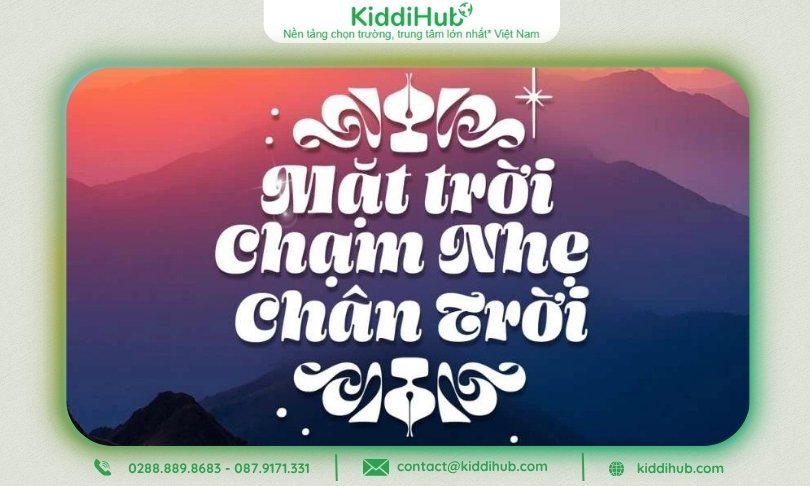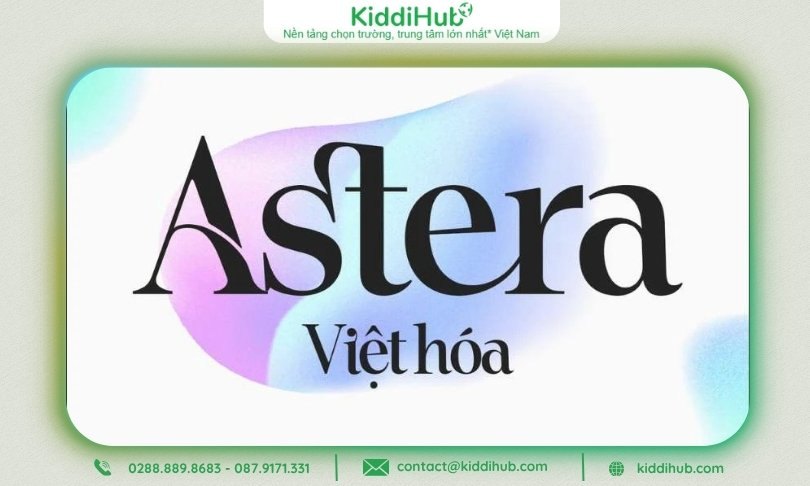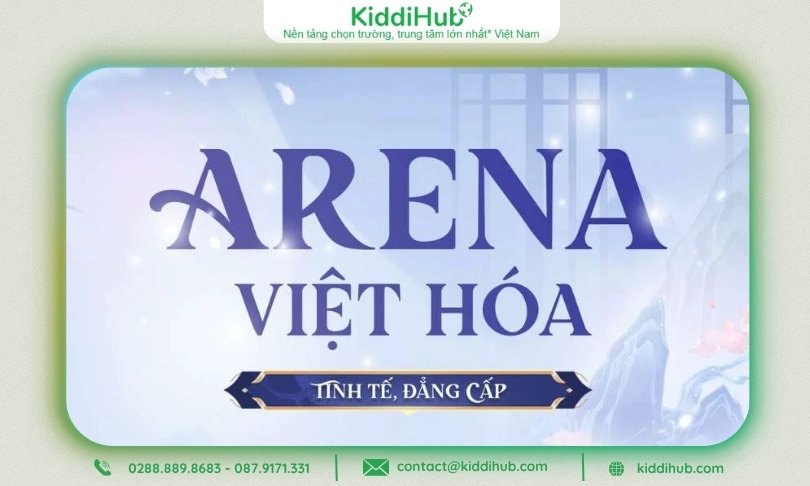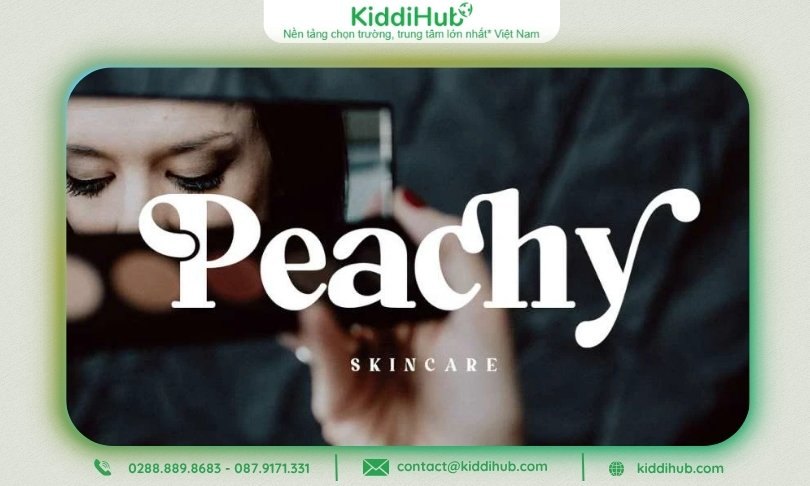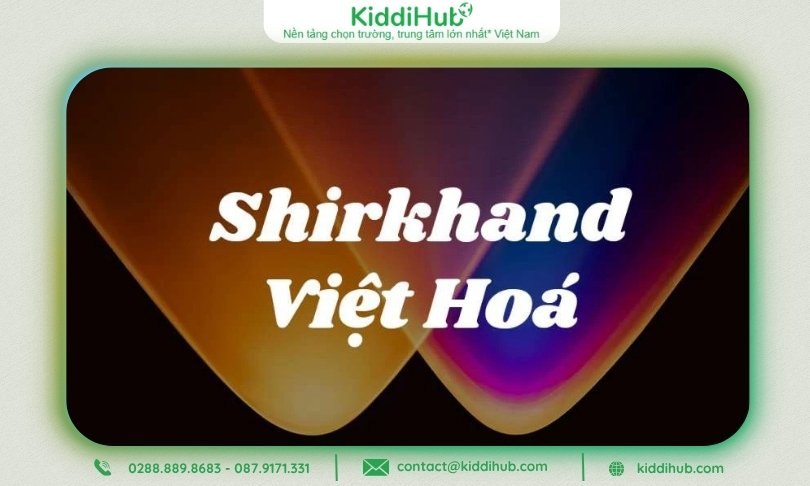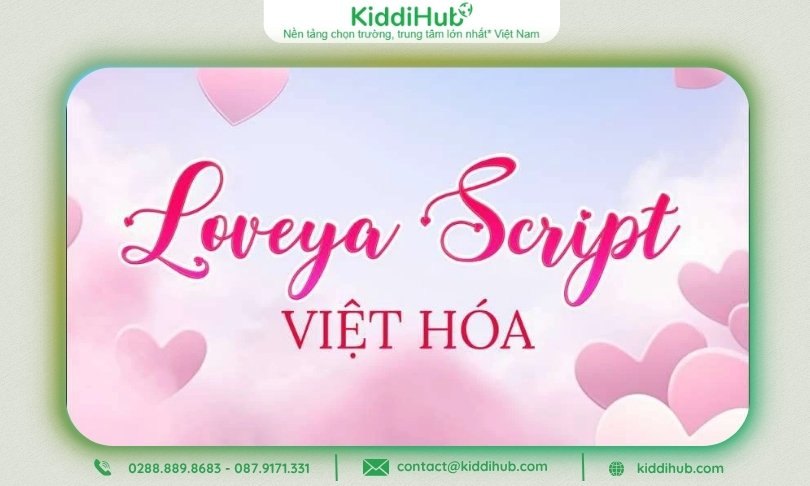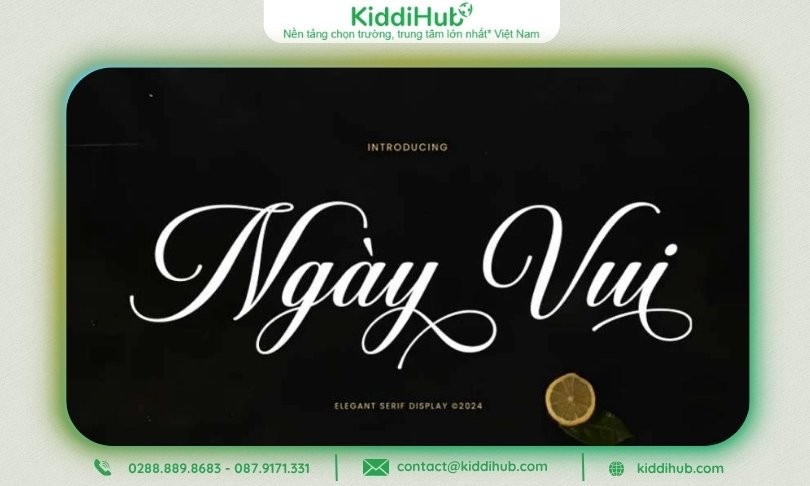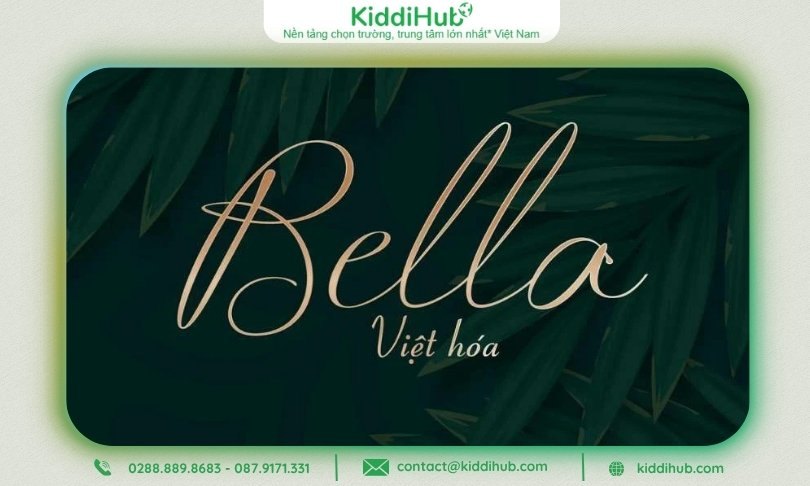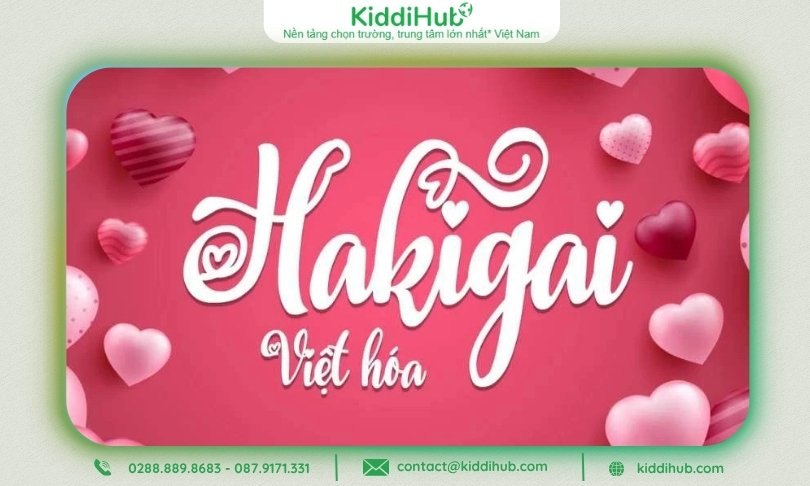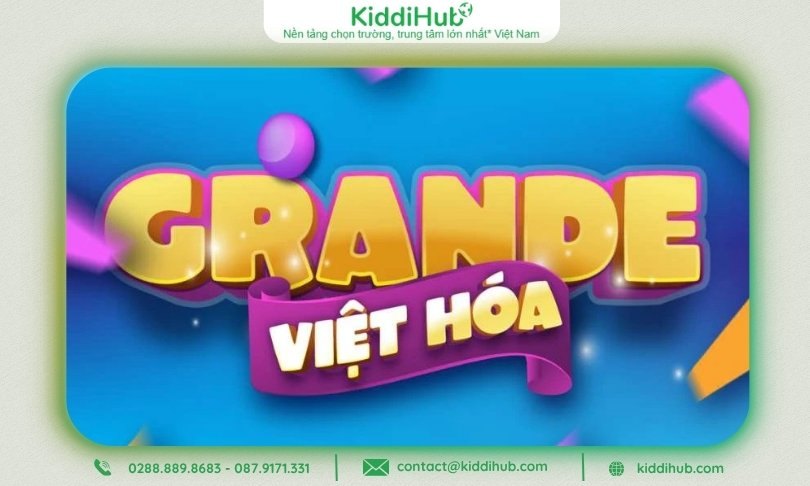
Font chữ 20/10 là chi tiết nhỏ nhưng lại mang sức mạnh lớn trong việc truyền tải cảm xúc. Dù là thiệp chúc, slide, poster hay video tri ân, lựa chọn đúng phông chữ sẽ giúp thiết kế thêm tinh tế & ấn tượng. Mỗi kiểu chữ đều có “tính cách” riêng – trang trọng, ấm áp hay trẻ trung – góp phần làm nổi bật thông điệp cùng với tinh thần tôn vinh phái đẹp ngày 20/10.
Tuyển tập phông chữ 20/10 Việt hóa dưới đây là “kho báu” cho những ai muốn tạo ra thiết kế chúc mừng đẹp, chuyên nghiệp trong năm 2025. Việc dùng font Việt hóa không chỉ giúp bạn gõ tiếng Việt có dấu mượt mà, tránh lỗi hiển thị mà còn giữ cảm xúc, tinh thần bản gốc của kiểu chữ.
Dù đang chuẩn bị thiệp mời, poster, slide công ty hay làm video tri ân phụ nữ, các font dưới đây đều mang nét riêng giúp tôn thông điệp của bạn.
DVN Lively là font script mềm mại, mang hơi thở nhẹ nhàng & thân thiện. Đường nét uốn lượn vừa phải, các chữ cái bo tròn tạo nên cảm giác gần gũi, tươi tắn.
Font chữ 20/10 này rất hợp với thiệp chúc, ảnh cover Facebook hoặc slide cảm ơn trong Ngày Phụ nữ Việt Nam. Khi phối, bạn có thể kết hợp DVN Lively với font sans-serif đơn giản như Montserrat hay Nunito cho phần nội dung để giữ bố cục hài hòa, hiện đại.
DVN Astera thuộc nhóm serif thanh lịch, có chân chữ nhẹ & tỷ lệ cân đối. Các chi tiết nhỏ trong chữ đem tới cảm giác tinh tế, rất phù hợp phong cách sang trọng, chuyên nghiệp.
Bạn hãy sử dụng Astera cho bìa thiệp mời, poster sự kiện công ty hay slide kỷ niệm. Khi đặt trên nền kem, vàng nhạt, hồng phấn, font chữ 20/10 này càng tôn lên vẻ trang nhã, thể hiện sự trân trọng dành cho phái đẹp.
Nếu bạn muốn gây ấn tượng mạnh ngay từ tiêu đề, DVN ARENA là chọn lựa lý tưởng. Font sở hữu độ dày vừa phải, đường nét mạnh mẽ nhưng vẫn có góc bo mềm để tránh cảm giác cứng nhắc.
ARENA rất hợp cho banner chúc mừng 20/10, poster sân khấu hoặc slide mở đầu. Đây là font chữ 20/10 giúp cân bằng giữa sức mạnh & sự tinh tế – tôn vinh hình ảnh người phụ nữ hiện đại vừa mạnh mẽ, vừa duyên dáng.
Sophia Beauty được thiết kế với cảm hứng từ sự dịu dàng & sang trọng. Kiểu chữ có độ cong mềm, giãn cách ký tự tinh tế, giúp cho thiết kế trông nhẹ nhàng mà vẫn cuốn hút.
Font chữ 20/10 này cực kỳ phù hợp cho logo thương hiệu mỹ phẩm, bìa thiệp hay ảnh tri ân. Khi kết hợp với hoa văn nhẹ cùng màu pastel(hồng phấn, be, hoặc lavender), Sophia Beauty tạo tổng thể tinh tế, đậm chất “feminine luxury”.
Shrikhand là font script đậm, nét dày & cực kỳ ấn tượng. Mỗi ký tự như có “trọng lượng”, tạo điểm nhấn mạnh mẽ, cuốn hút. Hãy dùng Shrikhand cho tiêu đề khẩu hiệu, slide mở màn video hay chữ trang trí trong poster.
Lưu ý, bạn không nên dùng font chữ 20/10 này cho nội dung dài. Hãy để nó làm “ngôi sao chính” trong bố cục để tôn trọng phong thái cá tính cùng sự tự tin của người phụ nữ Việt.
Font chữ 20/10 viết tay mang hơi thở truyền thống là chọn lựa hoàn hảo cho những ai muốn tạo thiết kế gần gũi, giàu cảm xúc & mang đậm dấu ấn cá nhân. Phông chữ viết tay không chỉ gợi lại hình ảnh của nét bút xưa – mộc mạc, chân thành – mà còn giúp lời chúc 20/10 thêm ấm áp, tinh tế.
Dưới đây là 3 kiểu chữ viết tay Việt hóa nổi bật, phù hợp cho thiệp, khung ảnh, slide video hay ấn phẩm tri ân trong dịp đặc biệt này.
Loveya Script mang phong cách viết tay nhẹ nhàng, các nét chữ nối liền mượt mà như dòng mực chảy. Font chữ 20/10 này có chi tiết nhỏ xinh như trái tim hay dấu chấm mềm mại, giúp thiết kế trở nên sinh động & giàu cảm xúc.
Phông chữ này rất thích hợp cho thiệp cá nhân, lời chúc dành cho mẹ, vợ hoặc người yêu. Khi dùng, bạn nên chọn kích thước chữ lớn cho tiêu đề, kết hợp với font sans-serif gọn gàng cho phần nội dung để tổng thể dễ đọc và hài hòa.
Peristiwa gợi nhớ nét bút thư pháp cổ điển, với độ dốc nhẹ cùng cấu trúc chữ chắc chắn. Cảm giác khi nhìn là sự trang trọng, mộc mạc – rất phù hợp cho lời chúc tặng mẹ, thiệp tri ân cô giáo hay sự kiện truyền thống trong trường học, công ty.
Khi in, bạn hãy chọn chất liệu giấy matt hoặc giấy có vân để tăng hiệu ứng “chữ in tay”, đem tới cảm giác sang trọng và chân thật.
DVN Bella là kiểu chữ thanh thoát, mảnh mai, mỗi nét như được viết bằng tay thật. Font chữ 20/10 này rất hợp cho lời chúc dài, đoạn thơ cảm động hay bìa sổ tay handmade.
Khi phối, bạn nên dùng nền sáng(be, trắng, pastel nhạt) và thêm họa tiết hoa lá nhỏ để tôn nét mềm mại của font chữ. Bella giúp truyền tải cảm xúc tinh tế – nhẹ nhàng nhưng sâu lắng, đúng với tinh thần Ngày Phụ nữ Việt Nam 20/10.
Đây là nhóm font giúp bạn “thổi hồn” cá tính vào từng thiết kế. Nếu font viết tay mang lại cảm giác mềm mại, truyền thống thì font sáng tạo lại là tuyên ngôn của sự mới mẻ, tự do & năng lượng tích cực.
Đây là chọn lựa lý tưởng cho poster trẻ trung, video chúc mừng hiện đại, chiến dịch truyền thông mạng xã hội hoặc ấn phẩm 20/10 muốn gây ấn tượng mạnh ngay từ ánh nhìn đầu tiên.